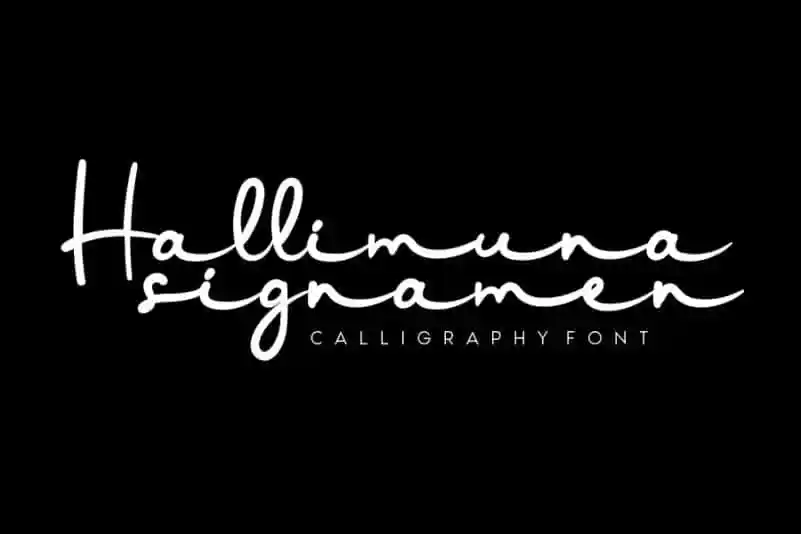
Hallimuna Handwritten Font – Fonte Grátis
Hallimuna Handwritten Font
Hallimuna é uma fonte escrita a lápis com traços suaves e muito relaxada. Seu design fluido permite que você use-a em uma variedade de aplicativos, como cartões de convite para casamentos, cartas de agradecimento, citações, cartões de boas-vindas, logomarcas e cartões de visita. A Hallimuna é perfeita para qualquer projeto gráfico que precise de um toque autêntico e pessoal. Seja ele uma festa especial ou apenas uma carta informal entre amigos, a Hallimuna oferece a opção ideal para deixar suas criações ainda mais únicas e personalizadas. Com este fonte escrita a mão, você pode criar trabalhos gráficos que se destacam do resto da multidão.